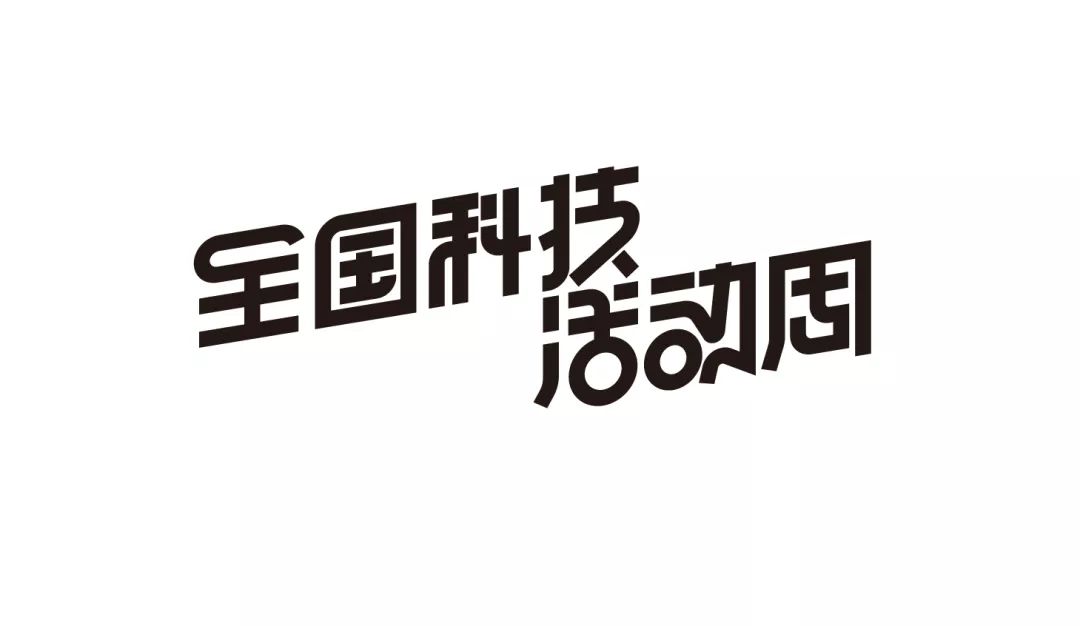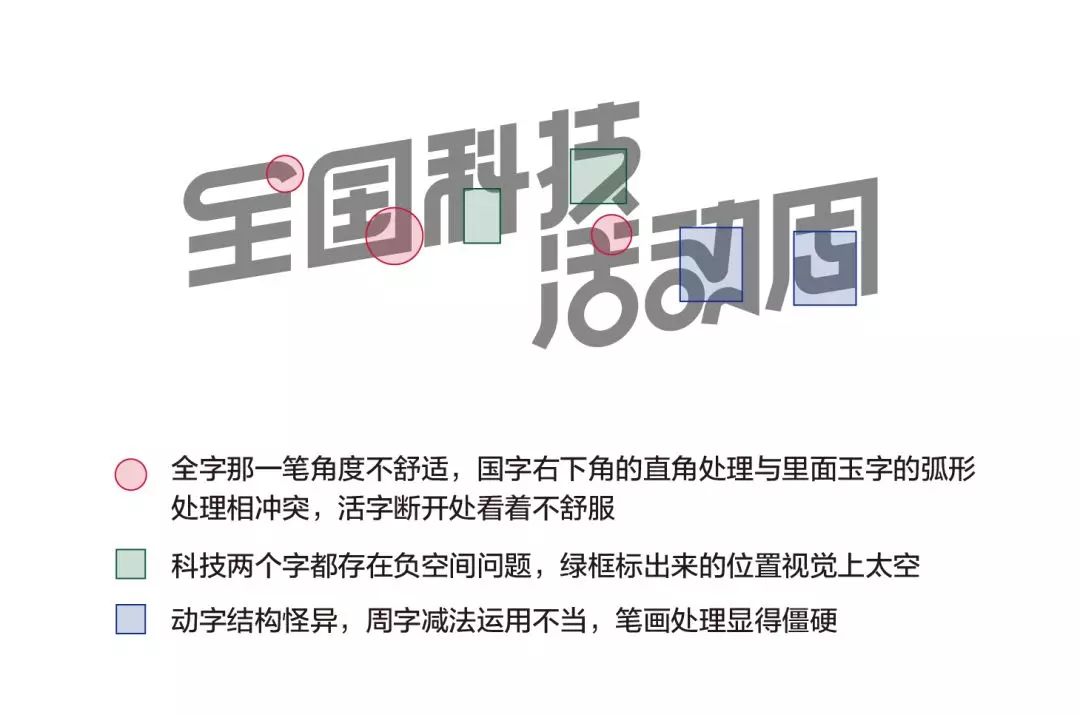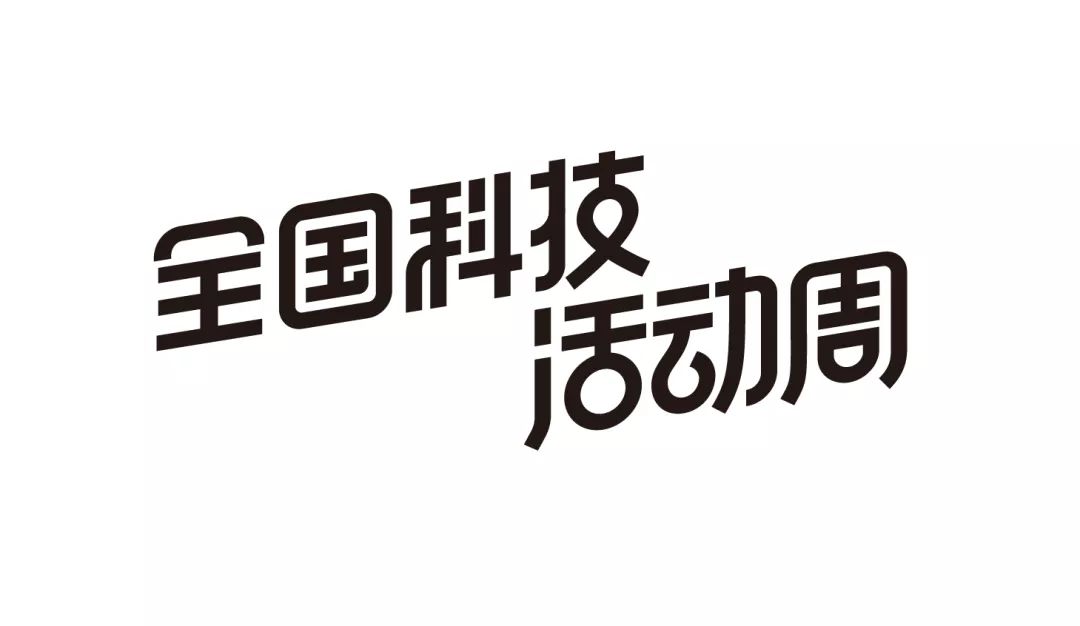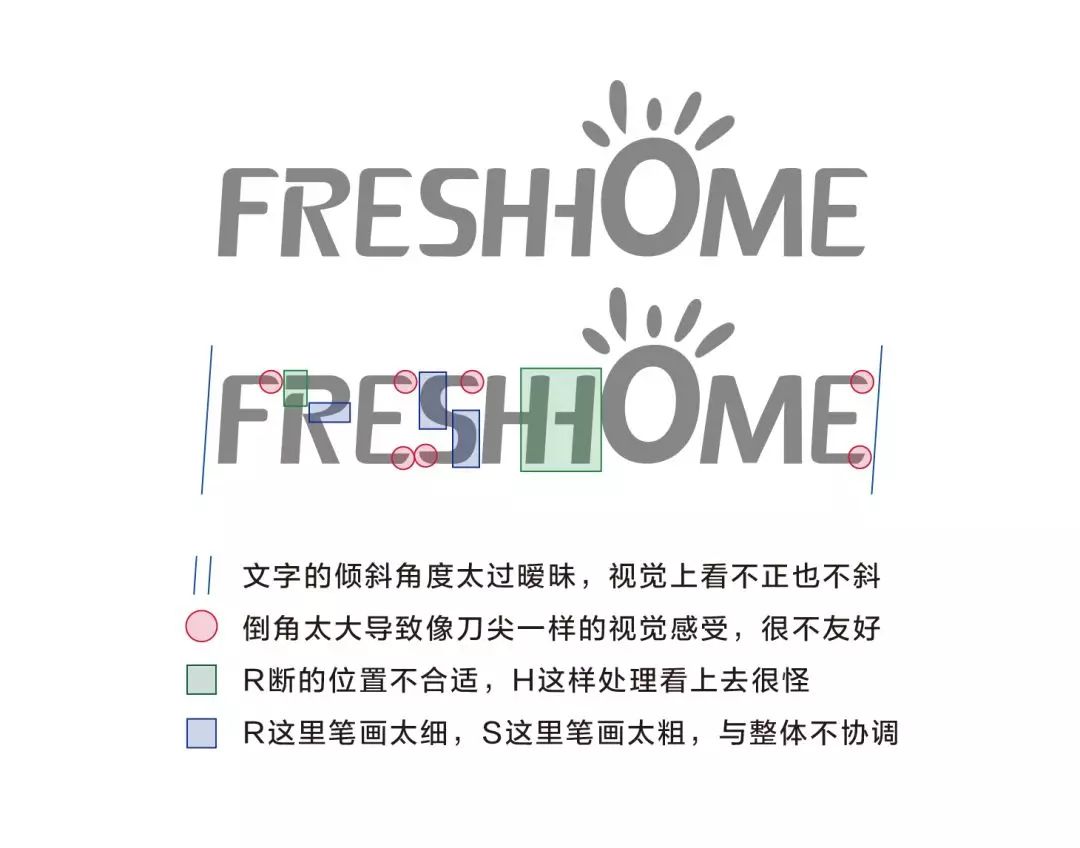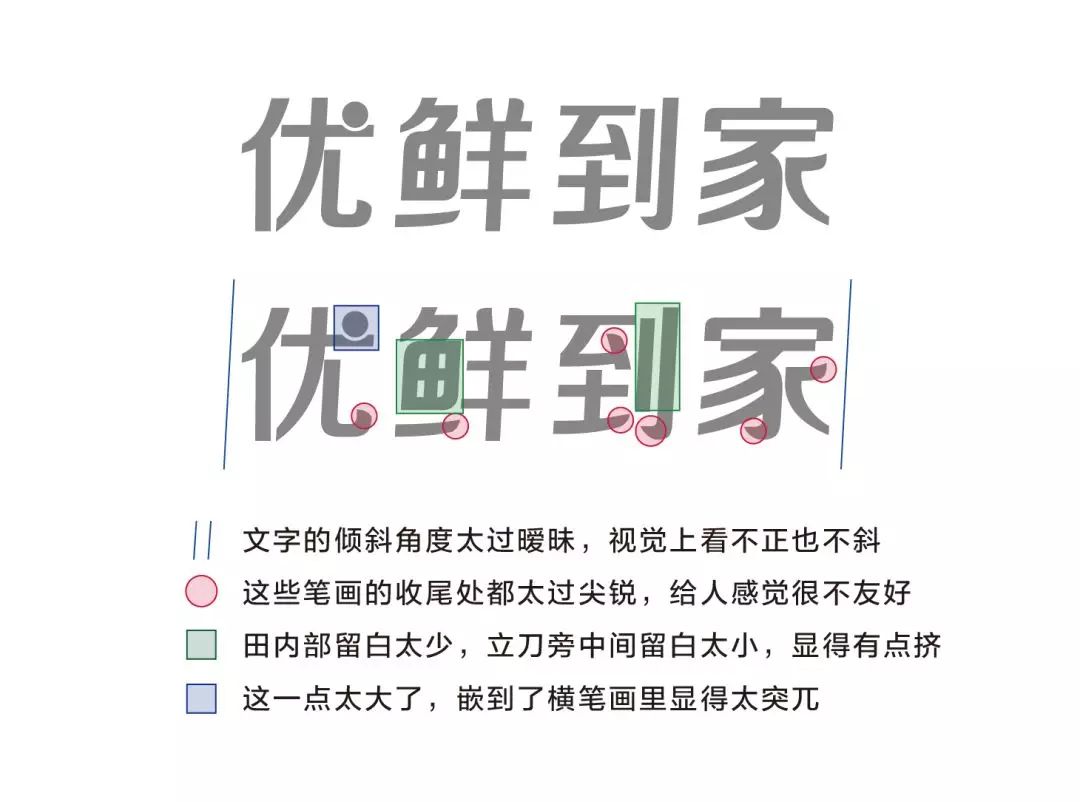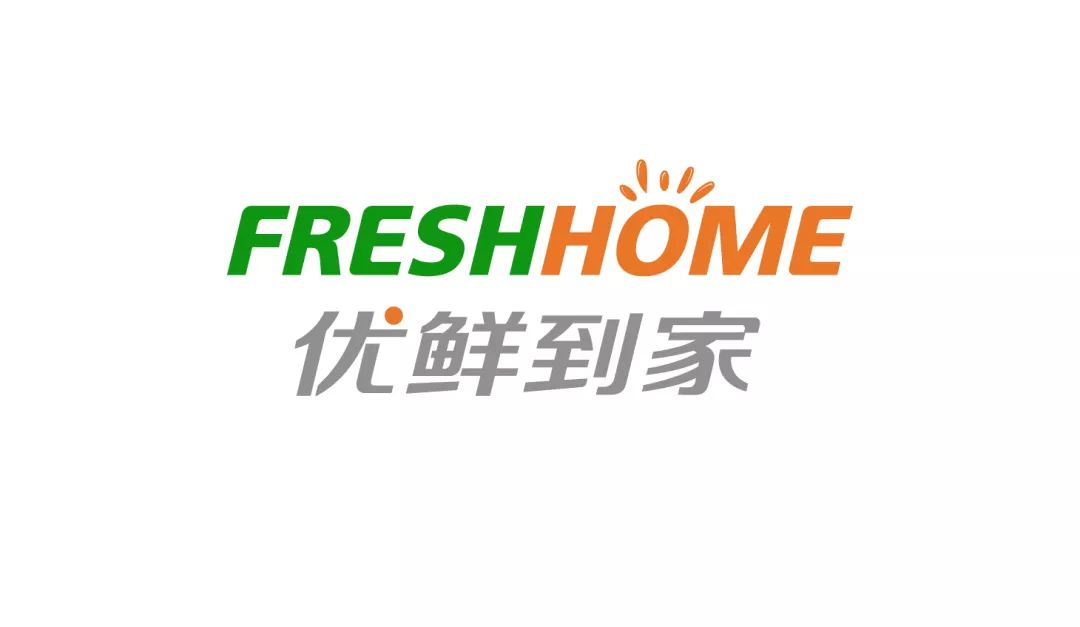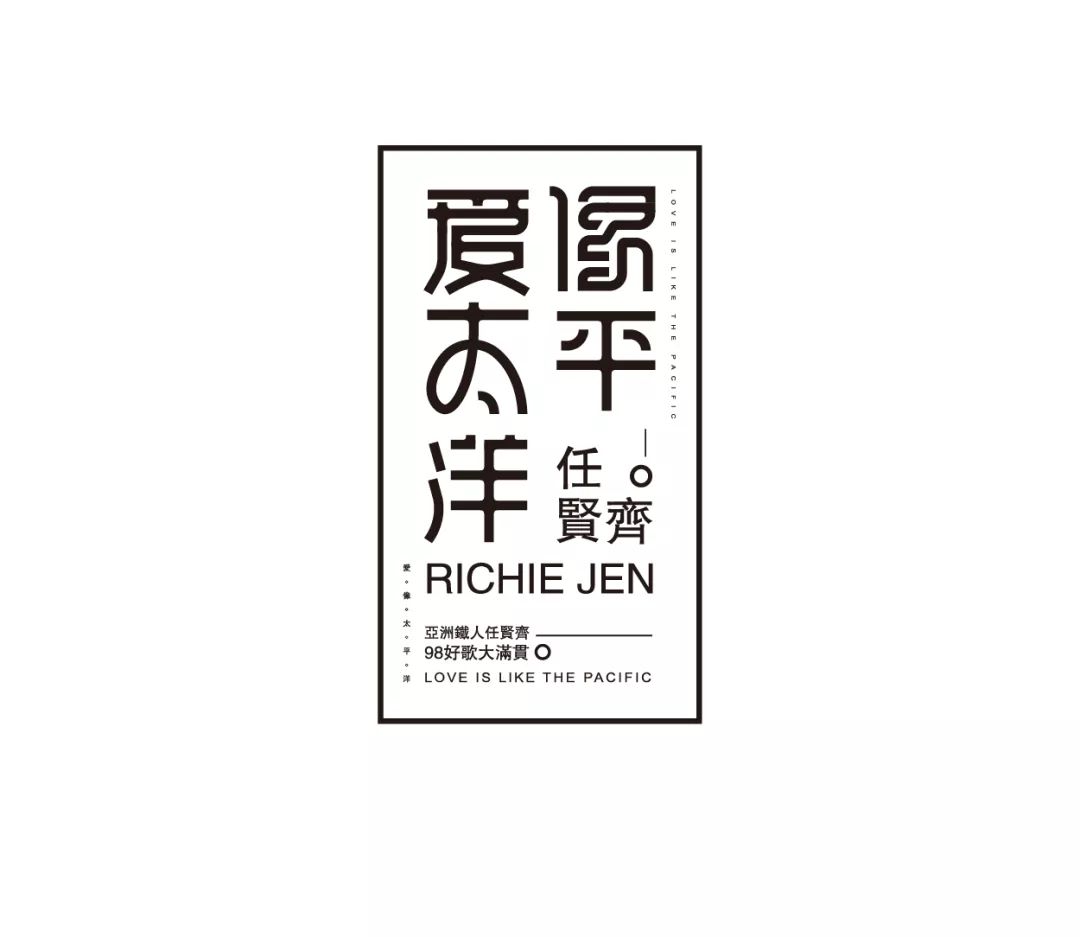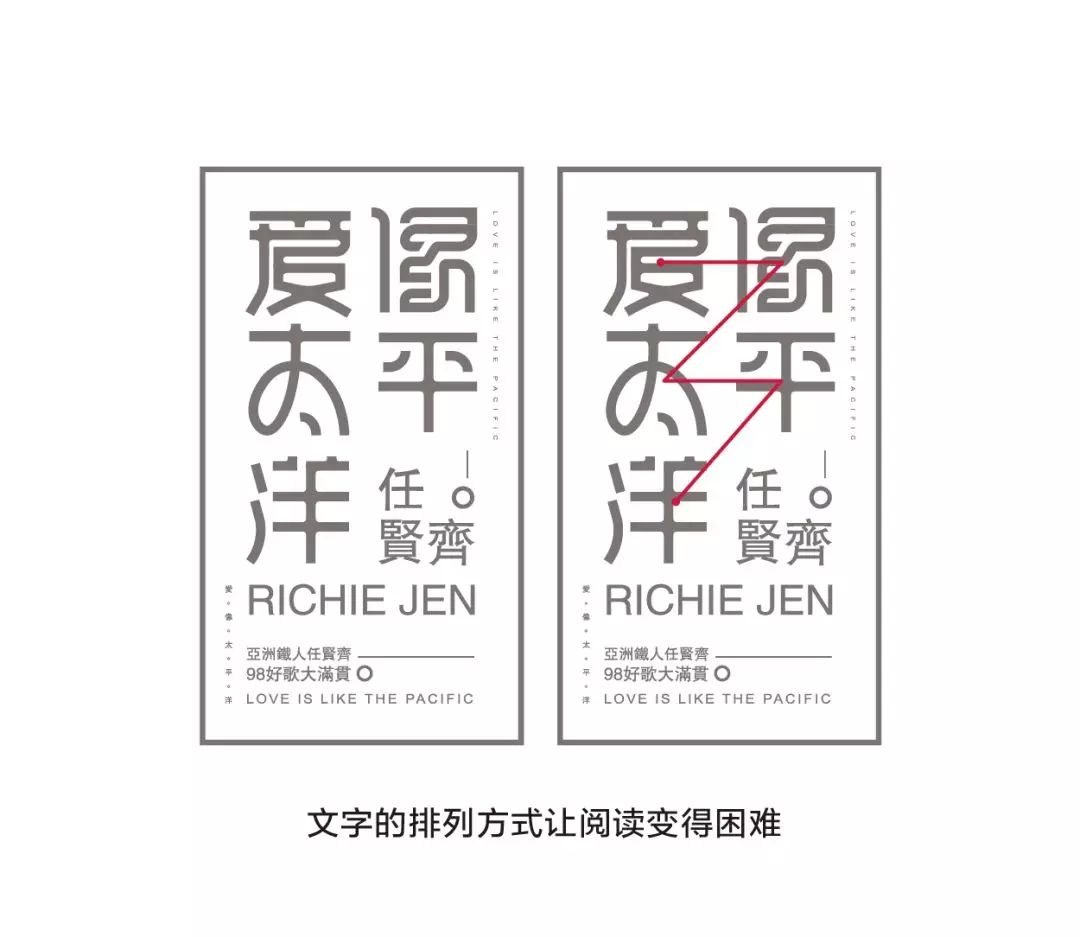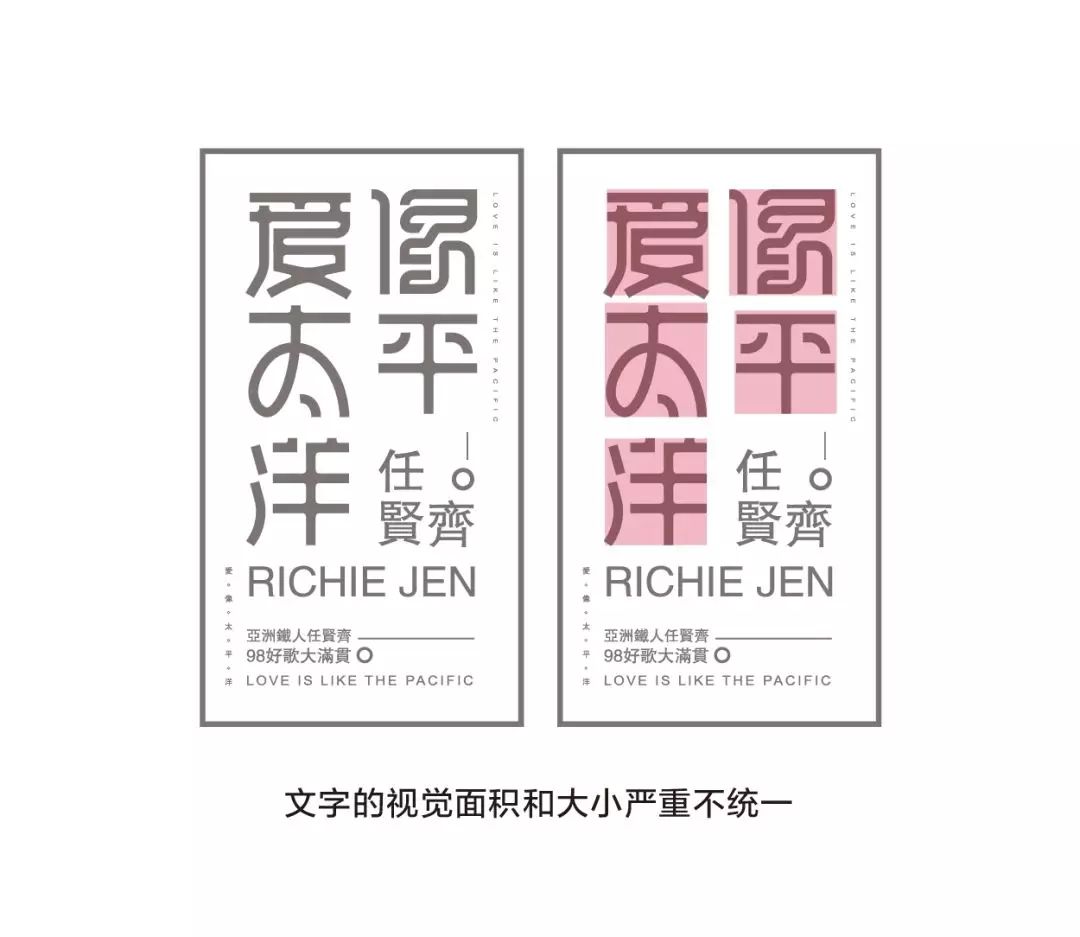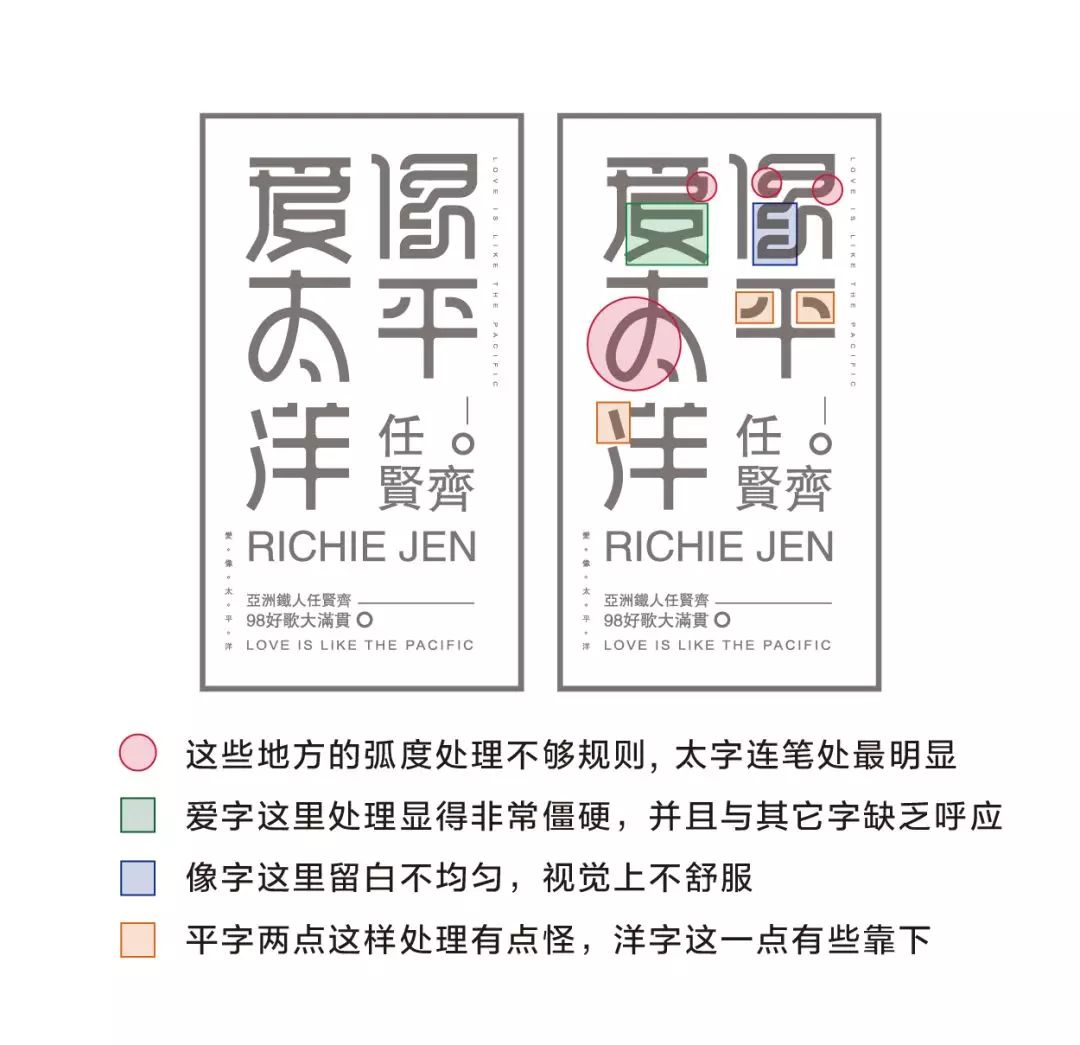
自我写教程以来,收到不少字友的关注,其中有不少字友会发字体作品让我帮其指点,但是单独言语上表述,不易让对方快速理解,一些微妙的地方也很难单独用文字表述清楚,于是我会挑选一些比较有代表性的作品去做修改,这期文章就来展示几个字友的作品以及我对其作品进行分析和修改的思路和过程。
案例一:全国科技活动周
这个字体存在的问题很多,也很明显,首先这几个字在视觉上不均衡,第一行“全国科技”中“科”字太小了,“技”字太大了,第二行“活动周”三个字“动”字比其他两个字显大了,造成这个问题的主要原因是正负形空间的安排不均衡;然后这几个字看着很别扭,在字体的结构上也存在较大的问题,下面我来做详细的分析:
首先看红色圆圈标注的地方:全字那一笔的收尾没有与下方的横笔画平行,造成负空间很难看;国字的右下角处理成直角和里面玉字的右下角圆弧处理不对应,视觉上相冲突;活动的活字断开的地方看着很别扭,显得笔画特别琐碎。
再来看绿色方框标注的地方:科字的中下方空白太大,视觉上形成一个很大的缺口;技字也一样,笔画省略的不恰当,标注位置形成很大的视觉缺口,看着很难受。
蓝色框标注的地方:动字的结构有些怪异,标注之处的笔画连接显得较为牵强;周字笔画省略不恰当,造成识别性下降,有点像固,且省略笔画后字形结构不美观。
通过分析以上问题,我设计了修正版本:
修正版本尊重了原作者的字形特点,对之前分析指出的问题进行了逐个修改:
“全”字左上的连笔去掉了,因为连起来有些怪,右上收尾处改成了与横笔平行的角度,视觉上舒服了很多;
“国”字的四个角都改为了适度倒角的圆角,与内部的玉字相协调;
“科”与“技”通过对笔画的修改解决了负形空间太大的问题,技字的笔画处理与下面的活动二字相呼应;
“活”字把笔画连上之后视觉上也舒服很多;“动”字笔画结构改为了符合书写规则的结构,视觉上更舒适;
“周”字改完之后,看上去更加友好,因为口字的处理像一个笑脸的感觉
来看一下对比:
案例二:优鲜到家
这个字体的问题也是很多的,首先第一眼视觉上就看到很多笔画粗细混乱不统一的问题,如英文部分“E”的竖笔画太细,“S”的竖向笔画显得太粗,“R”中间的那里笔画太细;还有就是横向笔画的粗细也很混乱;汉字部分“家”字笔画太粗,“鲜”字右半边笔画太细,还有很多细节问题,下面详细分析:
先看英文部分:
首先这个字体的倾斜角度太过微弱,看上去既不正也不太斜,这就比较尴尬,不但没有体现出速度感,反而给人的视觉感受是字有点歪。
红色圆圈标注位置:这些地方的笔画倒角太大,笔画的形状像一把尖刀一样,给人感觉不友好,视觉上也不美观。
绿色方框标注位置:“R”断掉的位置很奇怪,而且断笔处所形成的负空间视觉上不舒服;两个“H”这样处理看上去很怪,读起来也不连贯。
蓝色方框标注位置:“R”中间那一笔太细,与其它笔画无相应关系;“S”竖向笔画明显太粗,而且弧线的处理很怪,造成头重脚轻的视觉感受。
当然这个英文还有很多问题,就不一一列举了,初学者建议多多学习英文字体相关基础知识,推荐小林章的《西文字体》系列书籍,另外做的时候可以找一款经典字体去参考,不要盲目去设计西文字体。
好了,接下来我们看一下中文:
中文问题也不少,首先与英文一样存在倾斜角度太过暧昧的问题,看着好像字歪了。
红色圆圈标注位置:同样这些笔画的收尾处太像刀尖,与整体字形不协调,视觉上不美观,给人的感觉也不友好。
绿色方框标注位置:“鲜”字的田部分负空间太挤,导致田部分显得很重,右边的羊字反而显得太空,到字的立刀旁两竖靠的太近,视觉上有点挤。
蓝色方框标注位置:圆点太大,而且嵌入到了横笔画里显得很突兀。
接下来看一下我修改后的版本:
首先是字体的倾斜角度,明显体现出了速度感(从字意看应该是一个电商平台,所以配送速度应该体现),英文整体字形偏稳重给人信赖感同时细微的圆角处理体现出亲和力,中文部分使用了灰色,给人较为高端的品牌感受,整体字形较宽,显得稳重有信赖感,字形笔画简洁中加入适当的圆角,看上去很自然。
接下来我们看一下对比:
案例三:爱像太平洋
这个作品整体感觉还是可以的,排版比较整体,有细节,其中“像”字的处理方式很有创意且看上去不违和,但是问题也是很明显的,首先就是文字的排版方式有问题,让人读起来比较费劲,大家都知道中文分横排(阅读顺序从左到右)与竖排(阅读顺序从右到左)两种方式,像这种情况应该以竖排的形式去排版,现在这个排版会让人不知道怎么读,是“像平爱太洋”,还是“爱太洋像平”,还是“爱像 太平 洋”,所以说排版的时候一定要注意这个问题,读起来顺畅是很重要的。
第二个很明显的问题是“爱像太平洋”这五个字的大小严重不一致,“太”字明显太大,“平”字明显太小,“像”字比“爱”字高等视觉问题
接下来就是笔画问题了,“爱”字下方的“又”笔画上太僵硬,与其它字的笔画缺乏呼应;“像”字存在弧线处理不规则和负空间不均衡的问题;“太”字的连笔处曲线画的不规则,转角不顺畅;“平”字两点看着别扭;“洋”字左上那一点太靠下,详细分析如下图:
接下来看一下修改后的版本:
首先主文字的排版改为了竖排的形式,阅读上不再困难;然后这五个字在视觉上达到了大小的均衡;笔画处理上,“爱”字下方的“又”在笔画上与“太”字相呼应;“像”字调整了转角处的曲线弧度和负形空间;“太”字把连笔处的曲线处理的很顺畅;“平”字的两点改为对称形式,视觉上跟舒适;“洋”字左上角那一点向上加长,与右边更均衡,右边第一横与竖转折处加入圆角,在视觉上与其它几个字更为统一。
最后我们看一下修改前和修改后的对比:
原标题:字体设计-问题剖析与修改(2018年第一期)